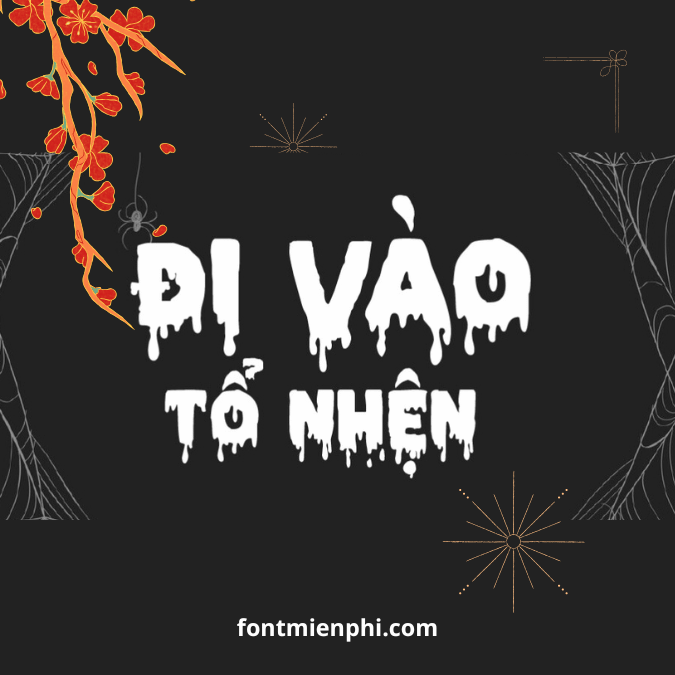
Font Việt hóa 1FTV VIP Pieces NFI ,Font Halloween
Font Việt Hóa 1FTV VIP Pieces NFI – Phông Chữ Halloween Rùng Rợn & Độc Đáo
1FTV VIP Pieces NFI là font chữ Việt hóa chuyên nghiệp với phong cách Halloween kinh dị, được thiết kế với những nét gãy vụn, vệt máu và hiệu ứng “tan rã” đầy ám ảnh. Font chữ này mang đến cảm giác ma quái, bí ẩn, hoàn hảo cho các dự án đậm chất horror.
Đặc điểm nổi bật:
✔ Phong cách rách nát, đứt gãy – tạo hiệu ứng như bị xé toạc, phù hợp poster phim kinh dị, game zombie.